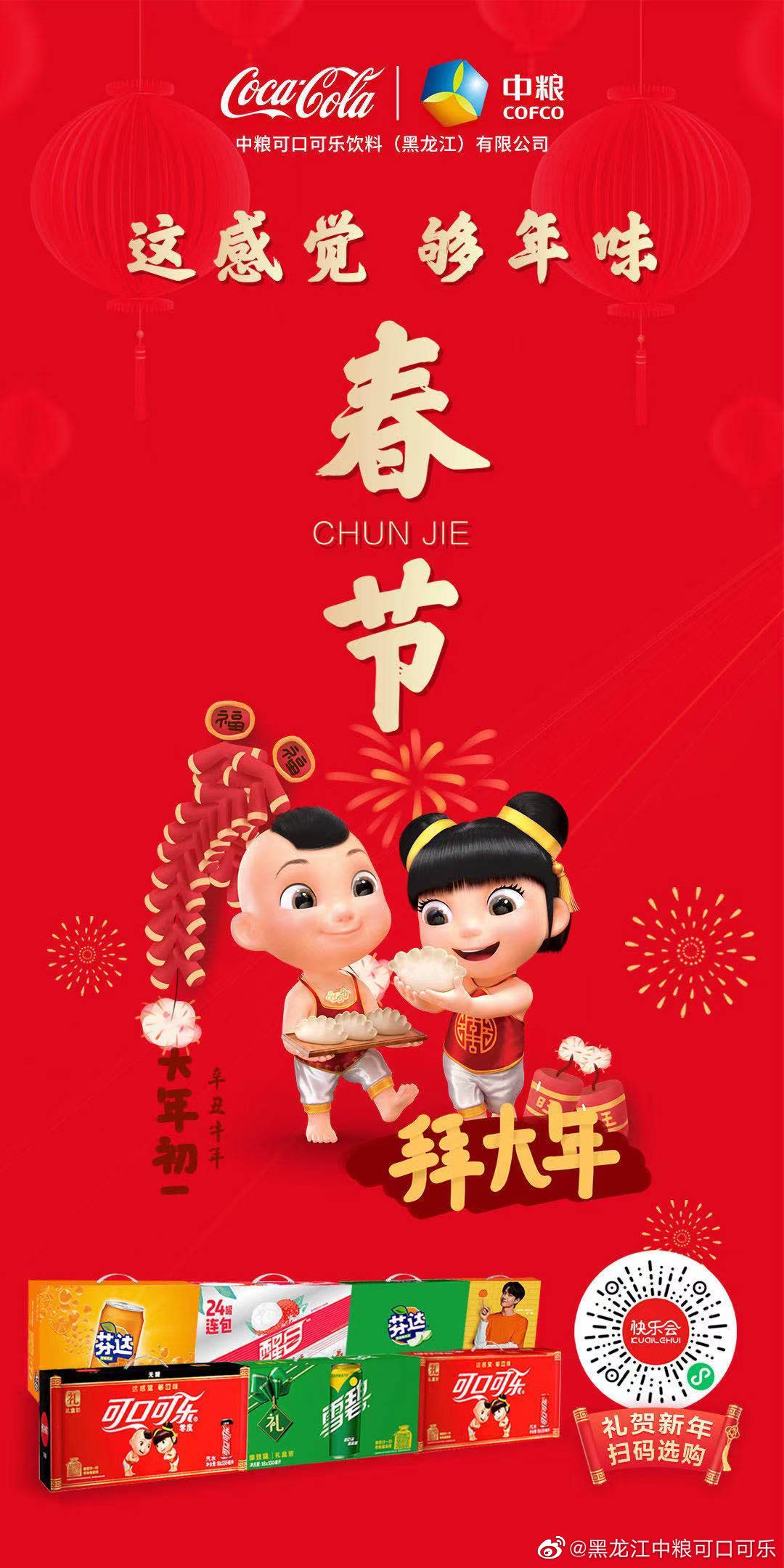
方正宋刻本秀楷家族
汤婷
宋体、楷书、混合
方正宋刻本秀楷复刻自宋代刻本《攻媿先生文集》。刻本中的楷体呈欧体风格,字形略为狭长、娟秀清丽,笔形瘦劲挺拔,刚健有力。尤其是横笔画微微上斜,笔画的起收转折已经初显“宋体”的演变端倪,兼有书写与雕刻的双重美感。方正宋刻本秀楷秉承宋版韵味,笔形忠实于雕版的手工痕迹,质朴、灵动,并按照当代字体的设计要求,在个性和规范之间做了很好的平衡。适合书籍、杂志的封面与正文用字,即便使用小字号也不会影响其易读性。2022年方正在单款宋刻本秀楷的基础上开发出6个不同粗细字重的家族字体。